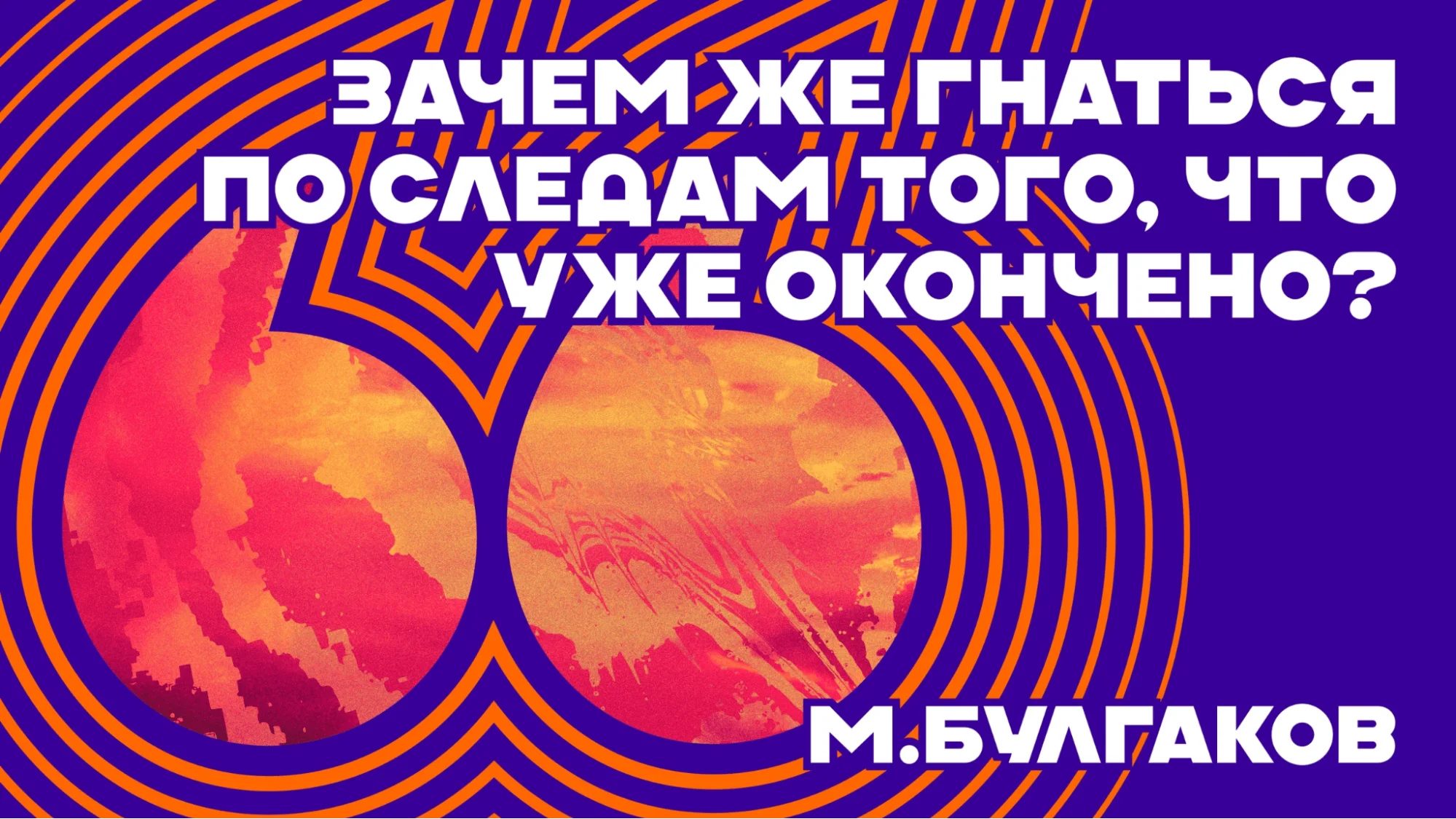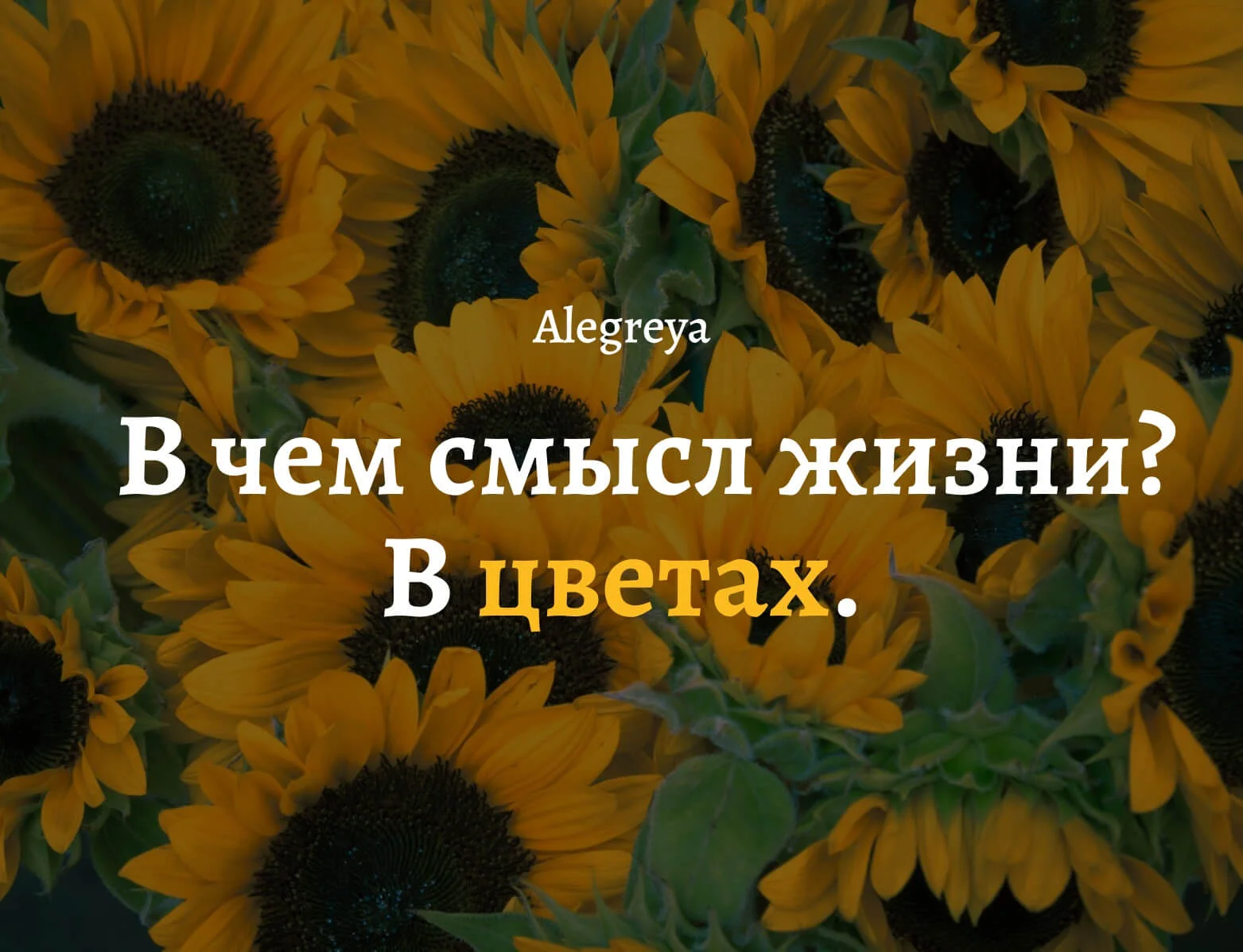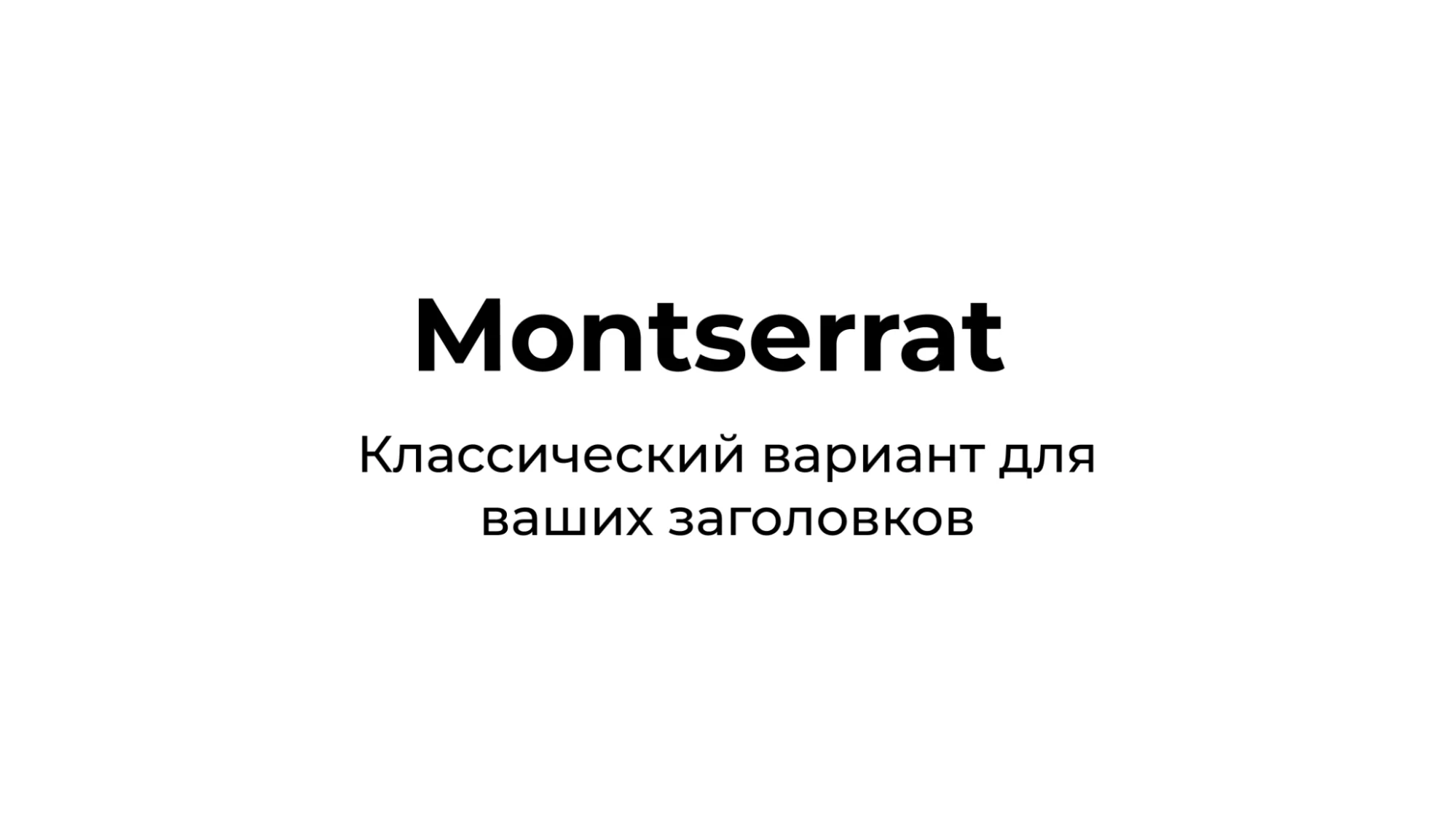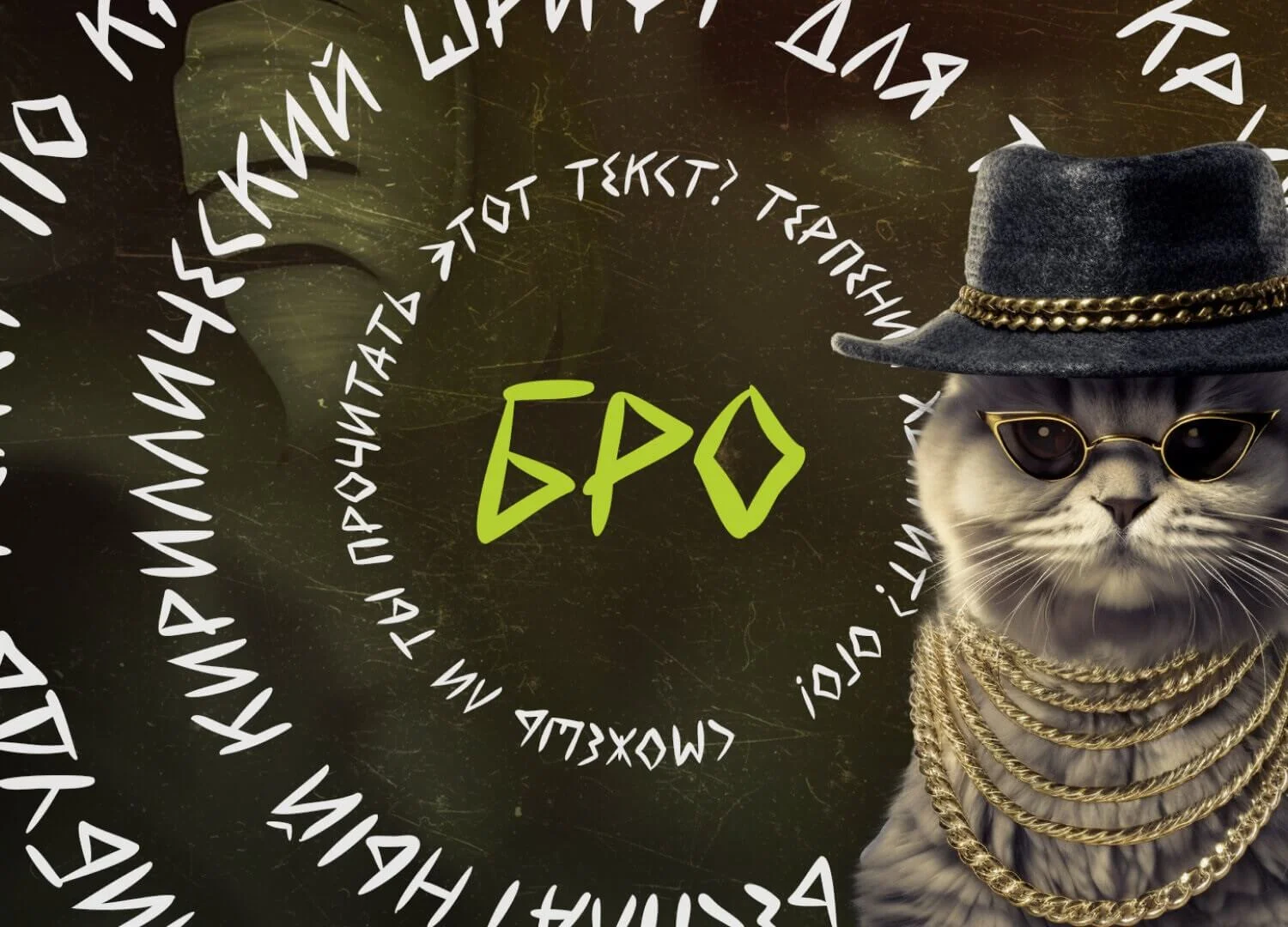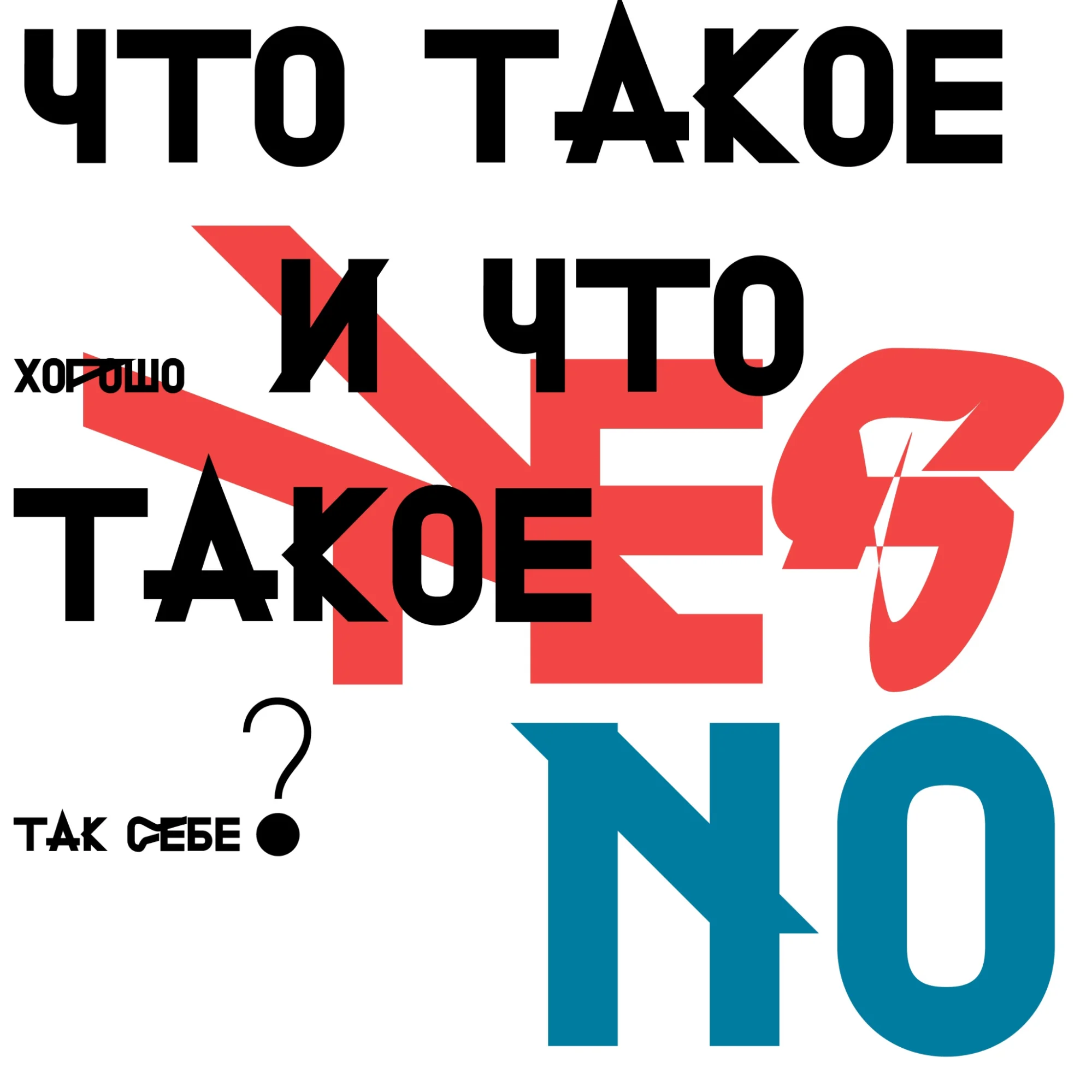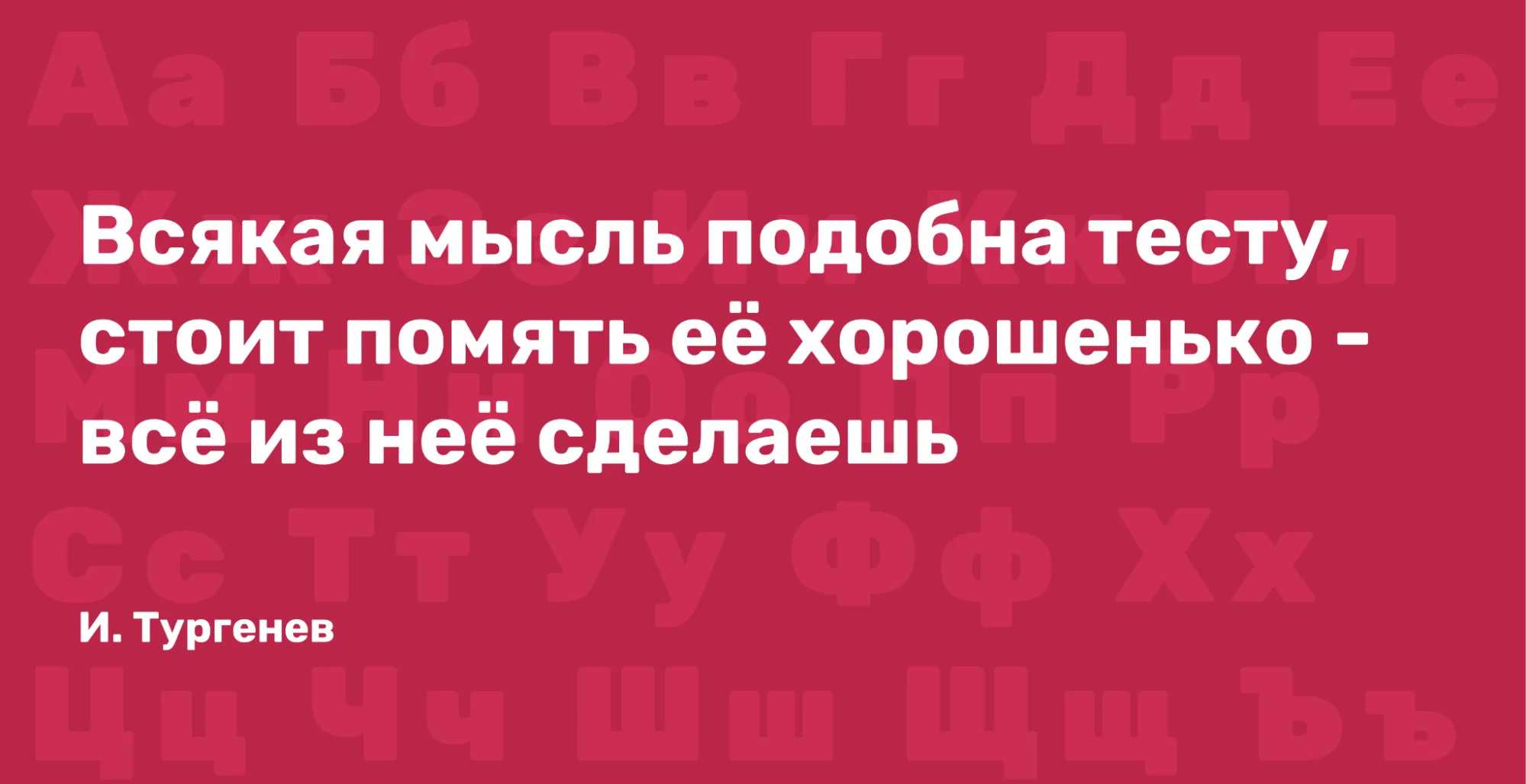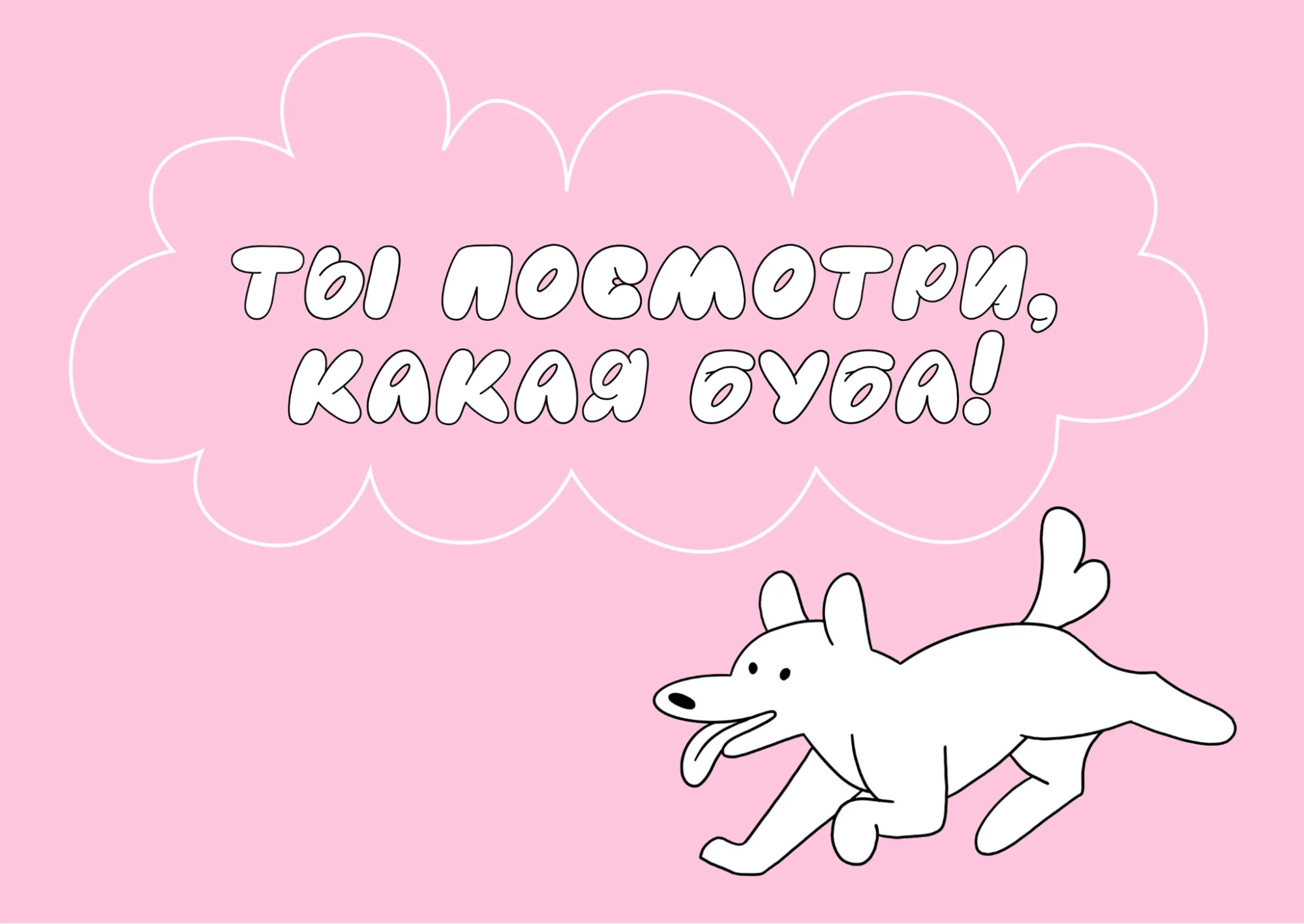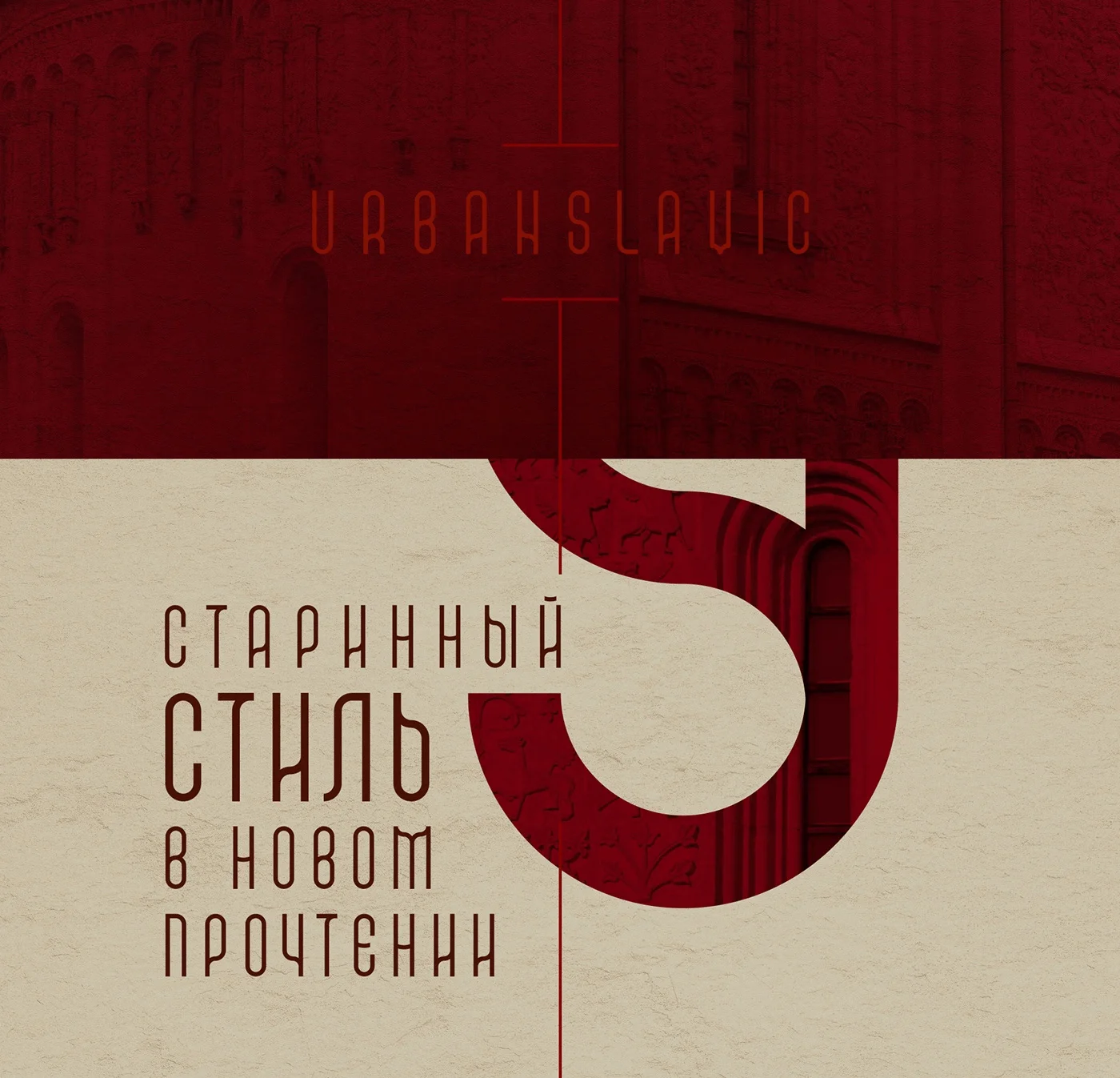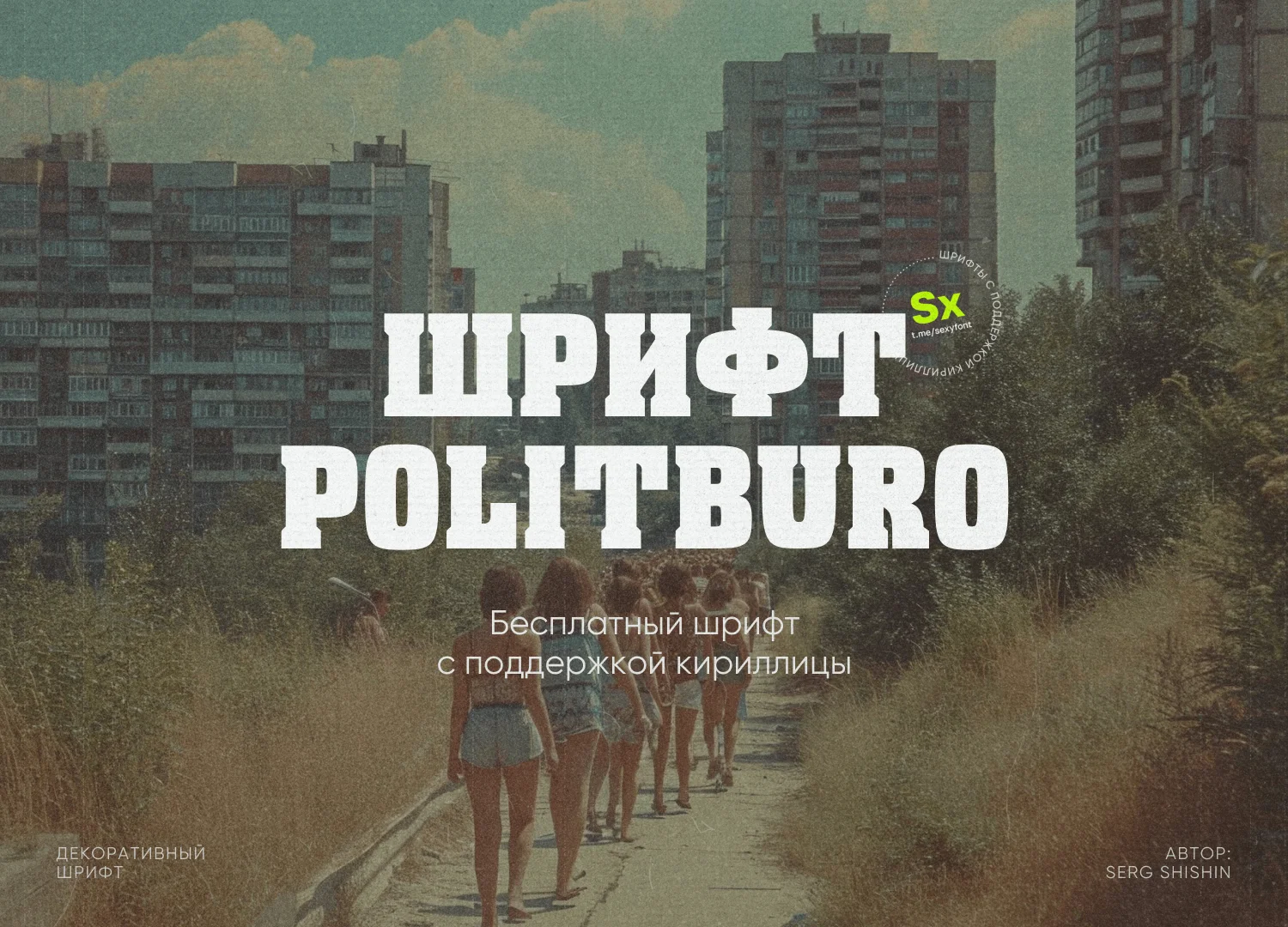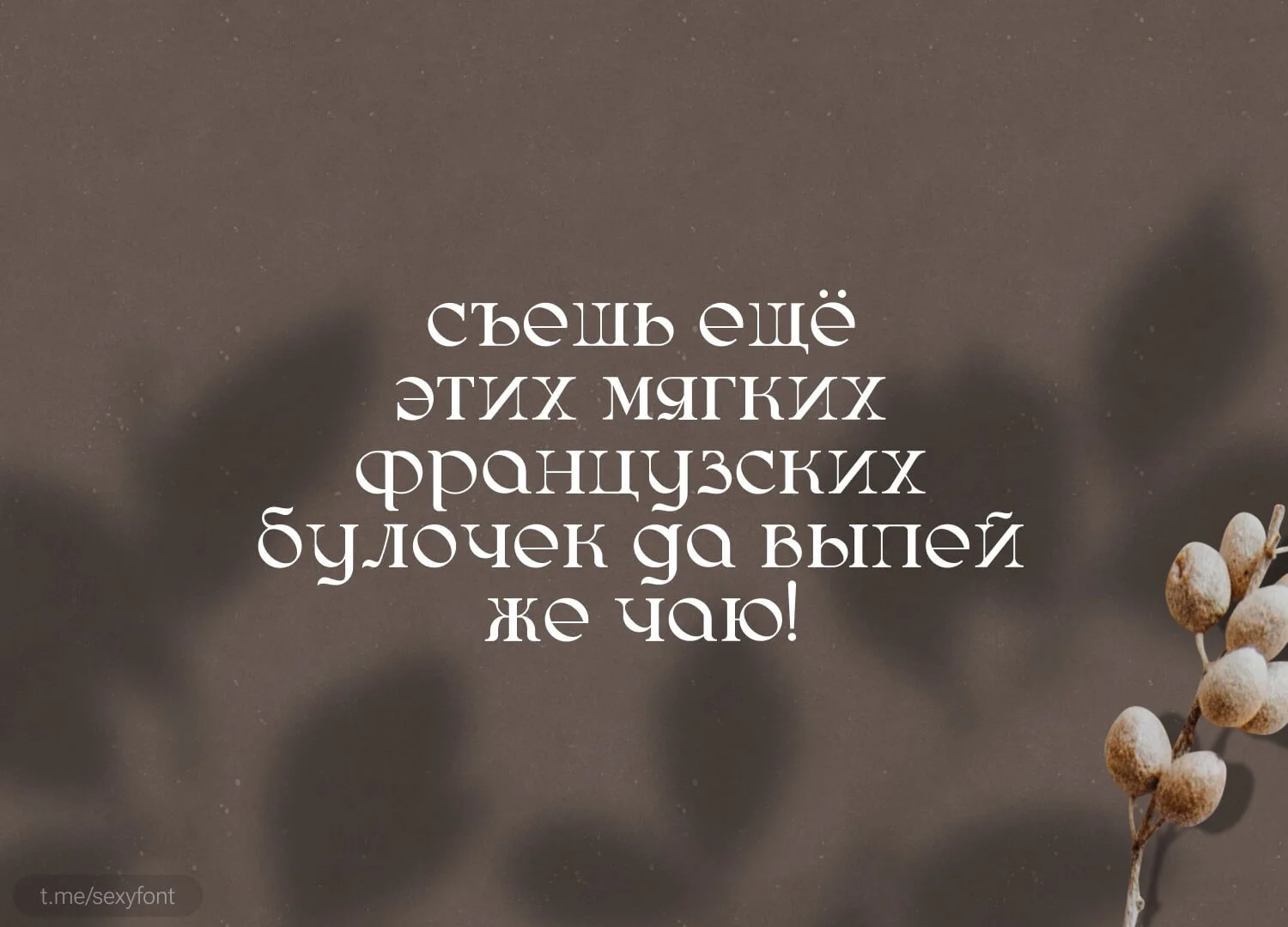
Сделайте текст заметным и запоминающимся
Шрифты — неотъемлемая часть брендинга, они помогают выделиться на фоне конкурентов и усилить впечатление от текста. Подбор правильного шрифта может быть непростой задачей. Мода быстро меняется, качественных бесплатных вариантов не так много и, возможно, их уже разобрали конкуренты. Но в нашей подборке вы точно найдете что-нибудь оригинальное. Мы собрали 20 бесплатных кириллических шрифтов, которые подойдут для создания броских запоминающихся заголовков и коммерческого использования.
| Заметные, но нейтральные и в меру строгие | Rubik, Playfair Display, Montserrat, Jost, Russo One |
| Имитируют письмо от руки | Mister Brush, Ruslan Display, Bro, Marck Script, UrbanSlavic |
| Изящные, с романтическим настроением | Bergamasco, Alegreya, Kreadon |
| Жирные с рублеными буквами | Raydis, GRUNT, Politburo |
| Иривые, с нестандартной формой букв | Buba, Press Start 2P, ST-Bubblegum, ST-Brigantina |
Шрифт Raydis — работа дизайнера Владимира Кленова. Отличительными чертами шрифта являются четкость и простота, что делает его идеальным для минималистичных дизайнов. Raydis может подойти для дизайна стартапов и инновационных компаний.
Шрифт без засечек Rubik разработан дизайнерами из Берлина специально для проекта Chrome Cube. Вдохновленный трафаретными шрифтами, Rubik сочетает в себе четкую геометрию и в то же время дружелюбный характер. Он отлично подойдет для современных минималистичных дизайнов, а чтобы придать заголовку еще большую выразительность, можно увеличить размер текста и выбрать контрастный цвет.
UrbanSlavic — шрифт, который погружает в атмосферу современного славянского граффити. Разработанный дизайнером Ольгой Кондаковой, этот шрифт сочетает в себе суровость уличного искусства с элементами славянской культуры. Лаконичные и выразительные буквы UrbanSlavic подходят для оформления музыкальных обложек или афиш городских мероприятий.
Politburo — геометрический шрифт с широкими и острыми буквами. Дизайнер Сергей Шишик создавал его, вдохновляясь советскими плакатами 1920-х годов. Он хотел передать дух эпохи, но в то же время сделать шрифт современным и универсальным. Сегодня Politburo можно встретить на обложках онлайн-журнала «Афиша».
Рукописный шрифт с небольшими штрихами и потертостями. Его автор, известный под псевдонимом GGBot, рисовал буквы маркерами и кистями, а затем оцифровывал их, сохранив естественную фактуру. Шрифт отлично подойдет не только для броских заголовков, но и для дизайна упаковки и ярких логотипов.
Kreadon — шрифт с угловатыми буквами. Некоторые буквы оформлены так, что между их линиями остаются небольшие промежутки. Это позволяет шрифту выглядеть необычно, но в то же время стильно и универсально.
Playfair Display — это антиква, то есть шрифт с засечками. Он создан Клаусом Эгереромм и вдохновлен шрифтами конца XVIII века. Однако некоторые особенности дизайна букв придают ему современное звучание. Playfair Display подойдет для элегантных заголовков в классическом и винтажном стиле.
Russo One — это современный гротеск от дизайнера Ивана Гладких, больше известного под псевдонимом Джованни Лемонад. Шрифт создан для тех, кто хочет придать дизайну смелый и дерзкий вид. Подойдет для заголовков, связанных с технологиями, наукой и космосом благодаря своему строгому и немного футуристическому стилю.
Bergamasco — шрифт с мягкими, округлыми формами и четкими засечками. Его разработал дизайнер Дмитрий Антонов. Шрифт обладает высокой контрастностью — между самыми тонкими и самыми жирными линиями большая разница, что придает буквам воздушности. При этом шрифт хорошо читаем. Bergamasco станет хорошим выбором для брендов, желающих выглядеть изящно и современно.
Шрифт с засечками Alegreya, разработанный Хуаном Пабло дель Пералем, сочетает в себе динамичность и элегантность. Alegreya подойдет как для набора основного текста, так и для ярких заголовков, особенно в большом размере. Шрифт доступен в нескольких начертаниях.
Шрифт без засечек Montserrat — геометрический гротеск, отсылающий к эстетике урбанизма. Дизайнер Джульета Улановски использовала в качестве прототипа старые вывески в районе Монсеррат в Буэнос-Айресе. В результате получился универсальный шрифт, который будет органично смотреться в дизайне практически любой компании.
Работа нижегородского дизайнера Александра Шиманова. В своем блоге он рассказал, что вдохновлялся произведениями автора детских книг Владислава Крапивина. Сам шрифт специфичный, местами неряшливый, что позволяет передать дух приключений.
Работа дизайнера из Санкт-Петербурга Анастасии Удовенко. Дутый шрифт, который не только хорошо сочетается с иллюстративной графикой, но и сам может быть главным элементом дизайна, привлекающим внимание. По словам автора, на создание Buba ее вдохновили винтажные упаковки жвачки и мультфильмы.